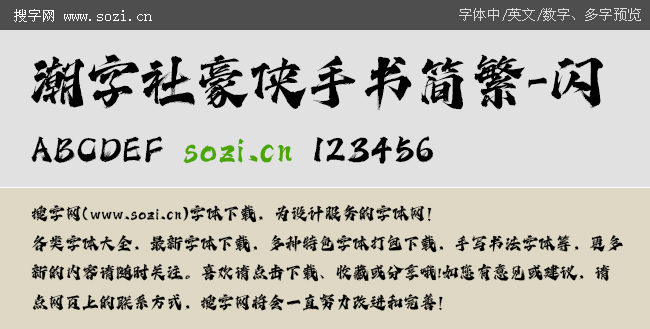
潮字社豪俠手簡繁-閃
搜字網(wǎng)提供一款潮字社豪俠手簡繁-閃中文字體下載,潮字社豪俠手簡繁-閃是一款非常獨(dú)特的個(gè)性毛筆藝術(shù)字體,這款字體字形瀟灑暢快的筆畫,豪放灑脫的字形,一筆一劃間,勾勒出漢字江湖的俠義風(fēng)情。適合應(yīng)用于藝術(shù)設(shè)計(jì)、平面宣傳設(shè)計(jì)、網(wǎng)頁設(shè)計(jì)等領(lǐng)域等應(yīng)用。。(本字體為個(gè)人非商用版,商用請聯(lián)系作者購買授權(quán)。官方網(wǎng)址:http://www.reeji.com 聯(lián)系方式:021-58597892)